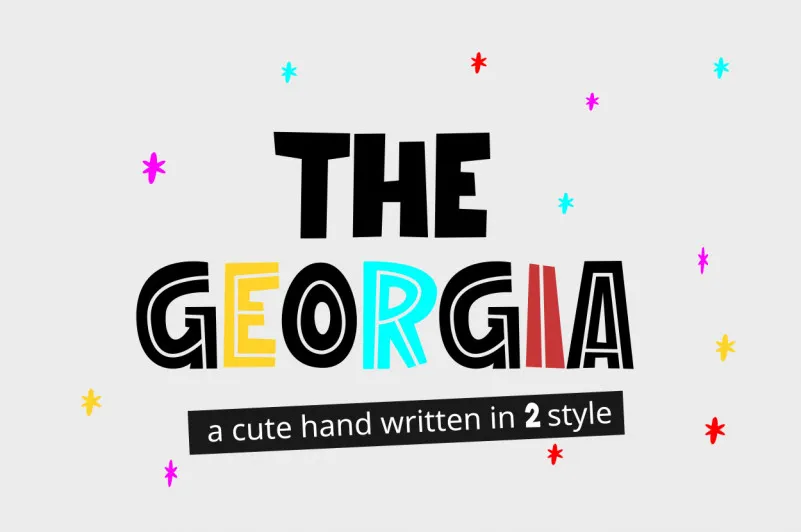
The Georgia Font – Download Grátis
Descubra a elegância pura da Georgia Font para seus projetos digitais com estilos clean e moderno. Projetada pelo designer sugiharto1790, esta fonte sem serif oferece uma aparição sofisticada que transmite confiabilidade. Com linhas leves e um design minimalista, a Georgia é perfeita para gráficos de sites, e-mail marketing, publicações digitais e muitos outros usos. Ela traz uma combinação perfeita de elegância e facilidade de leitura, tornando-a uma escolha ótima para qualquer projeto que deseje manter-se profissionalmente atraente. Experimente Georgia hoje, e transforme seu design em um elemento ainda mais poderoso.
Designer: sugiharto1790